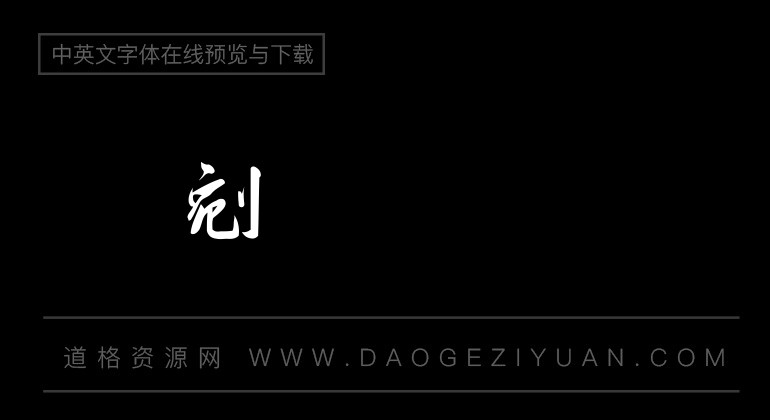
金梅毛笔匾行书是一种传统的中国毛笔字体,它来自汉代,历经几千年的发展,现在仍然是中国书法的主流字体。它的特点是极其细腻的笔画,书法家可以根据自己的喜好,加以变化,而不会影响字体的整体美感。金梅毛笔匾行书的笔画简单,曲折,节奏明快,非常适合用来书写标语、匾额等。文件名:JinMeiMaoBiXingShu-1.ttf
金梅毛笔匾行书是一款非常不错的手写艺术字体,具有很好的视觉感,适合于文化类的宣传设计、商业类品牌的广告和产品包装设计以及个性化文字排版等较多场景。